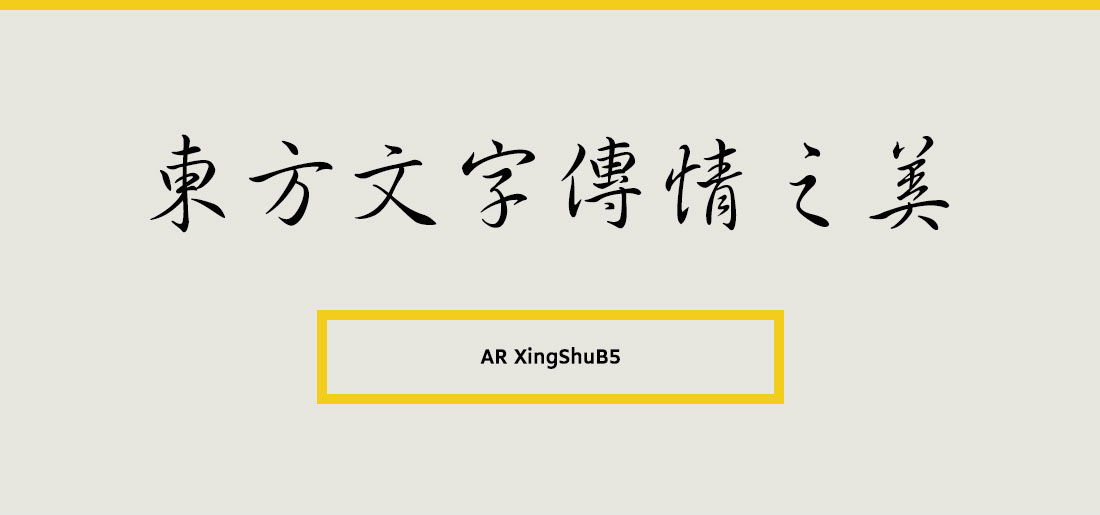
- XingShuB5는 붓펜 타입의 글씨체로 서법의 올바름과 조화로움, 유려함이 더해져 한자의 아름다움을 표현할 수 있는 폰트이다.선이 가늘고 길게 표현되며 글자의 흐름을 따라가는 독특하고 다양한 방법을 제공해 작업자의 다양한 선택을 도와 준다.폰트명 뒤에 붙은 B5라는 표기는 번체의 문자코드인 BIG5를 뜻한다. 번체란 중국을 제외한 대만, 홍콩, 마카오 등의 중화권 국가에서 사용하는 전통적인 모양의 한자다. 중국에서 사용하는 간체(GB)와는 달라 잘못 적용할 경우 글립이 제대로 표기되지 않거나 다른 글립으로 표기되는 문제가 발생할 수 있다.